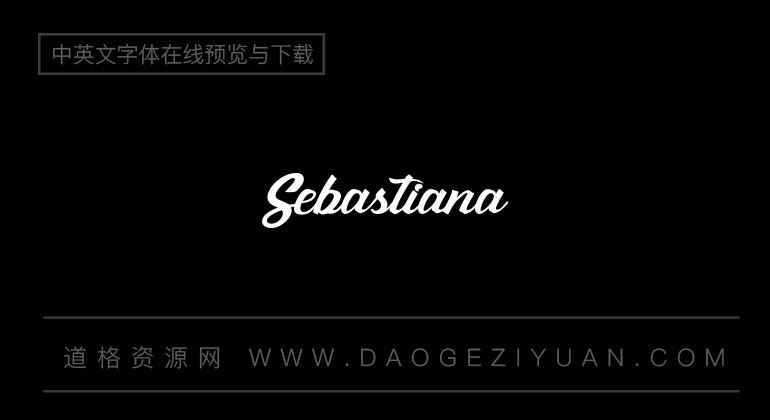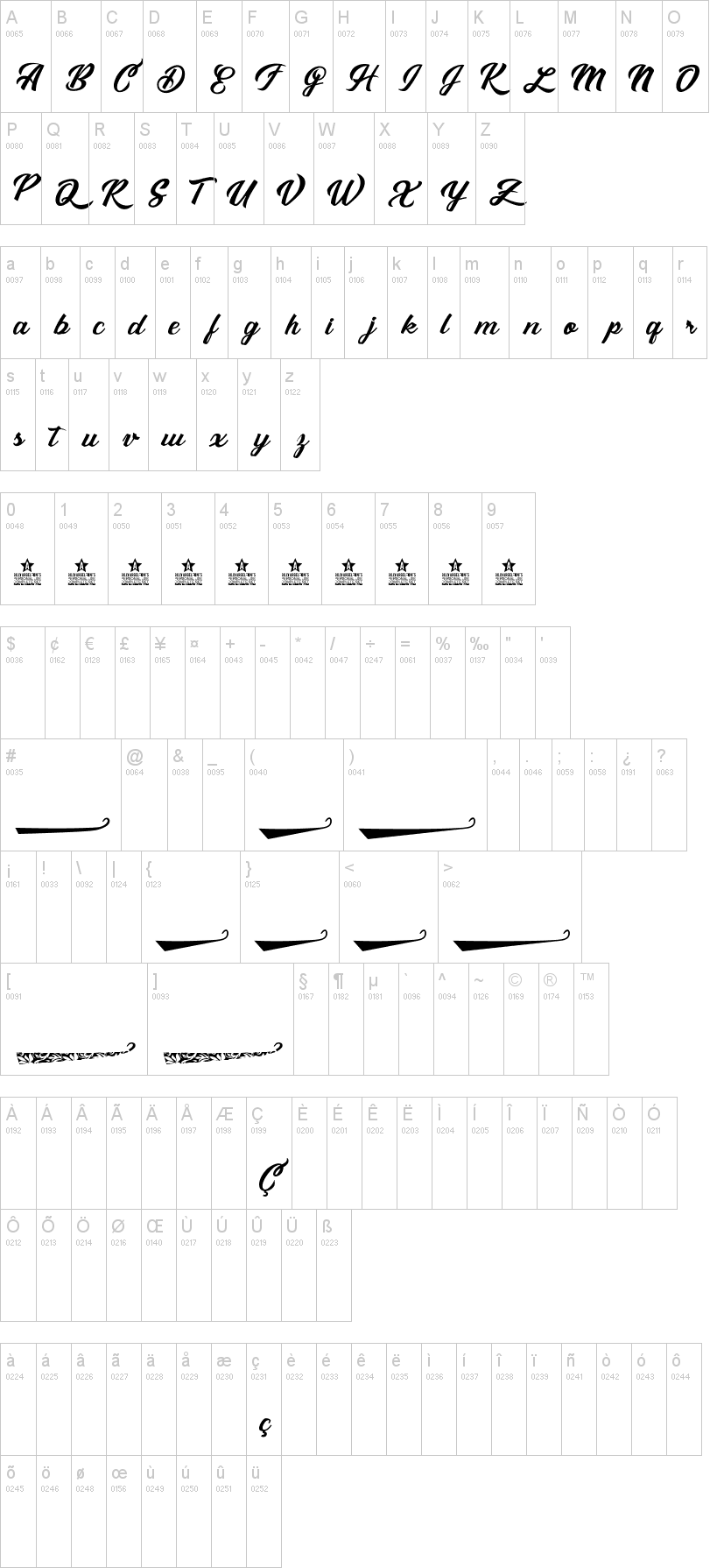
Sebastiana 是一款有趣的手写字体,它具有古典复古风格,具有流畅的线条和优雅的曲线。字体的设计源自古老的西班牙文字,以及西班牙文化的精髓,充满活力和热情。字体的每个字母都有一个独特的设计,从粗细的线条到精致的装饰,都能为文字添加活力和情感。Sebastiana 字体可以用于各种应用,如标题、标签、标语、海报、海报、海报等,为文字添加活力和情感。内容介绍
Sebastiana是一款非常不错的手写艺术字体,具有很好的视觉感,适合于文化类的宣传设计、商业类品牌的广告和产品包装设计以及个性化文字排版等较多场景。